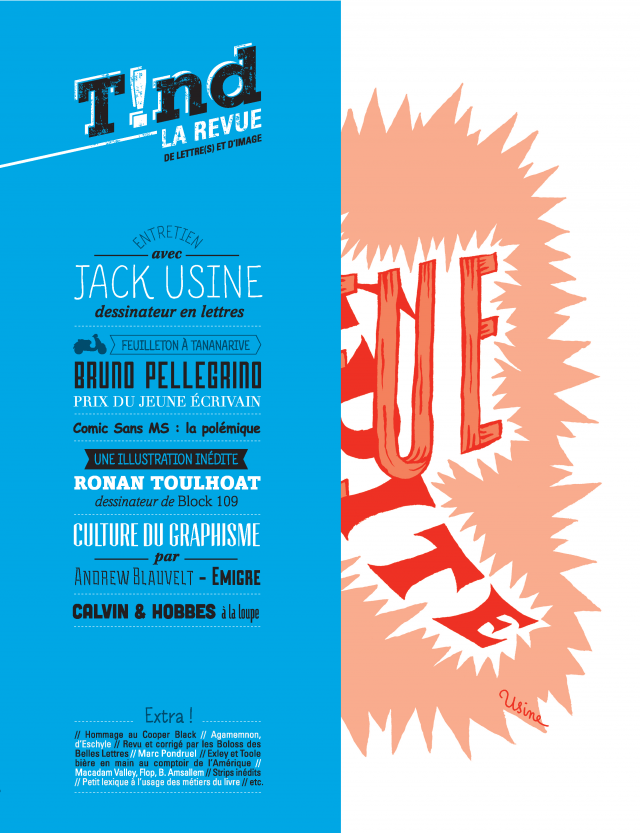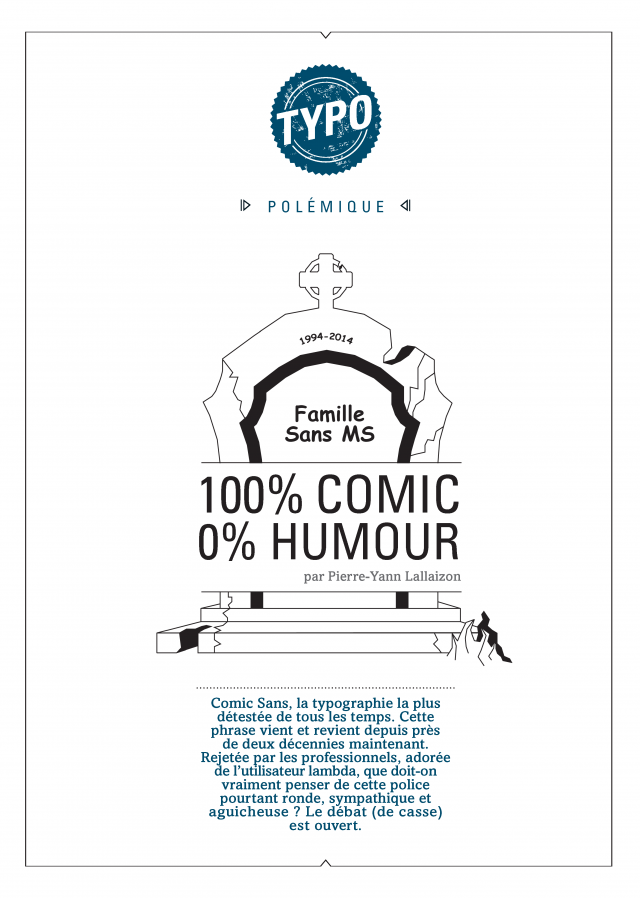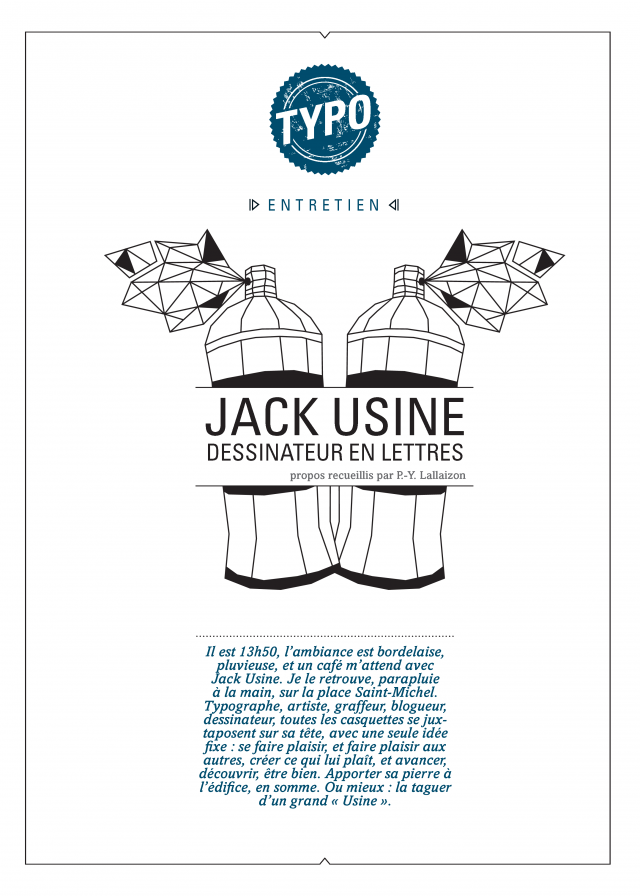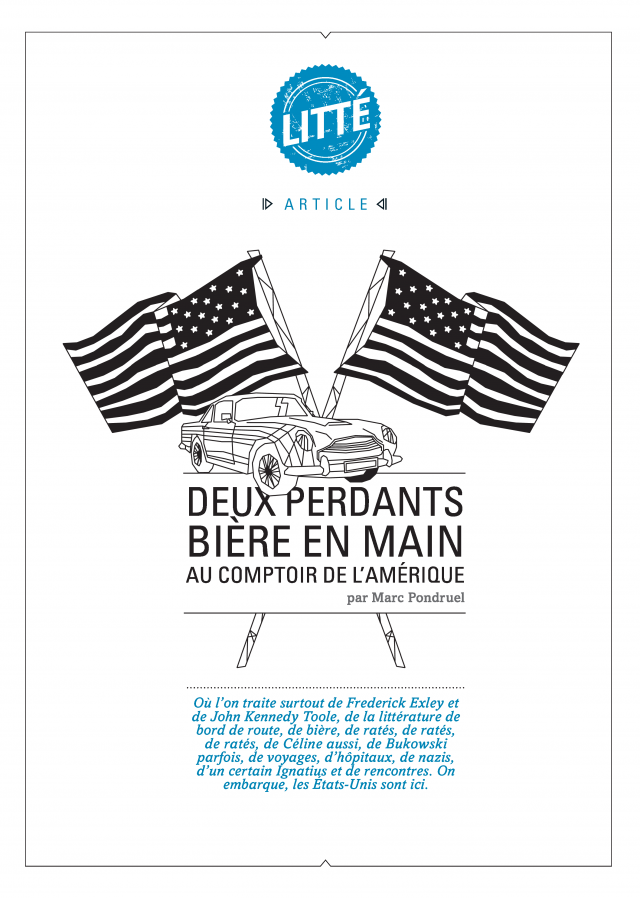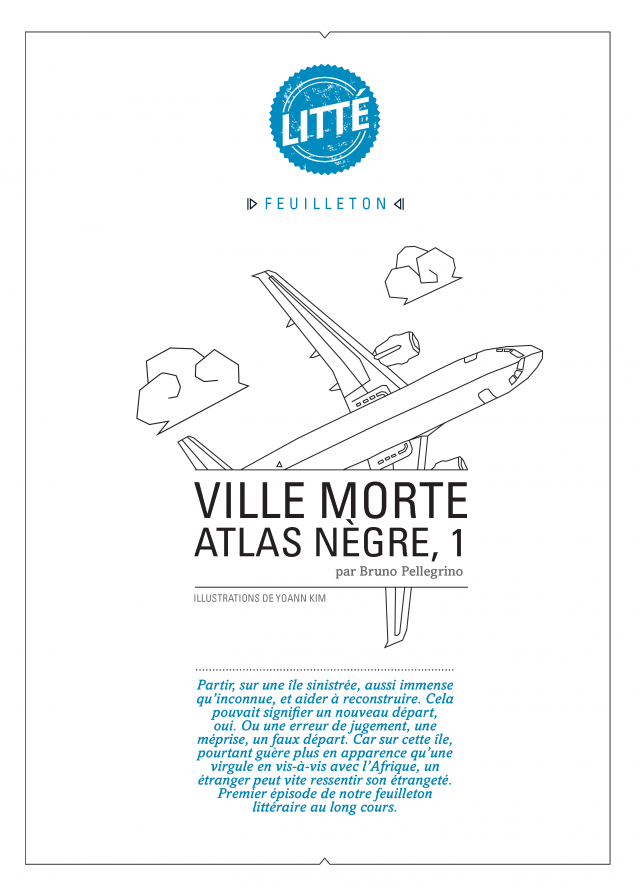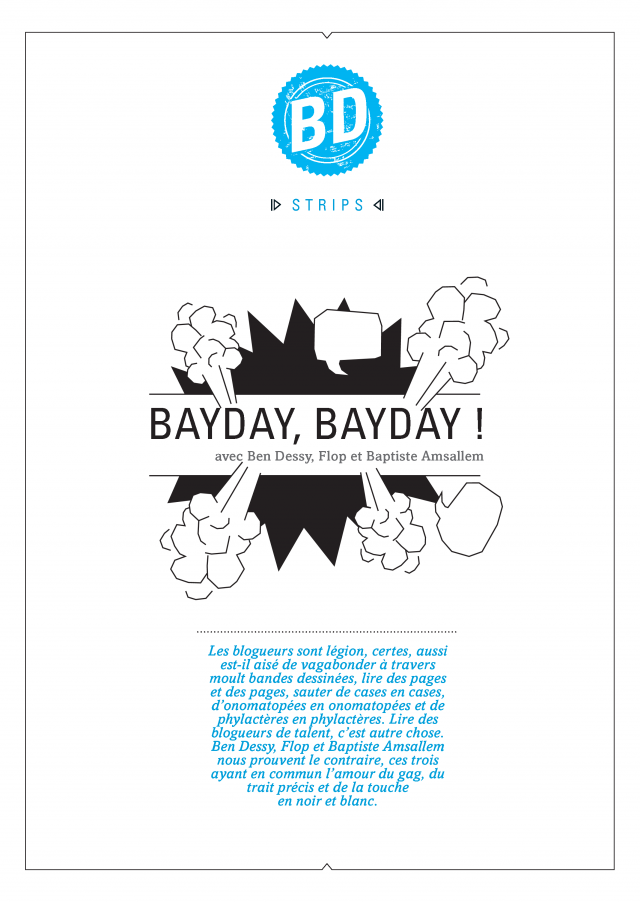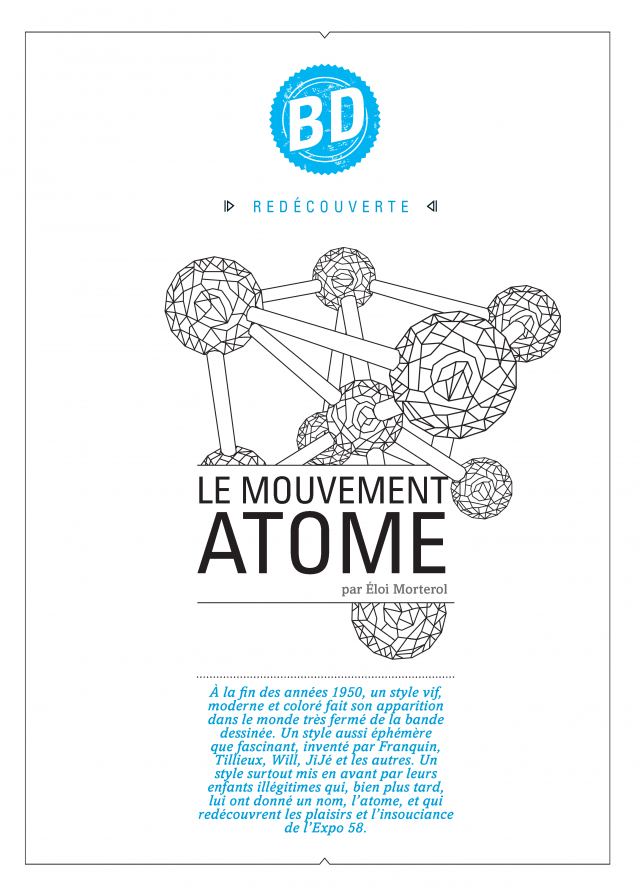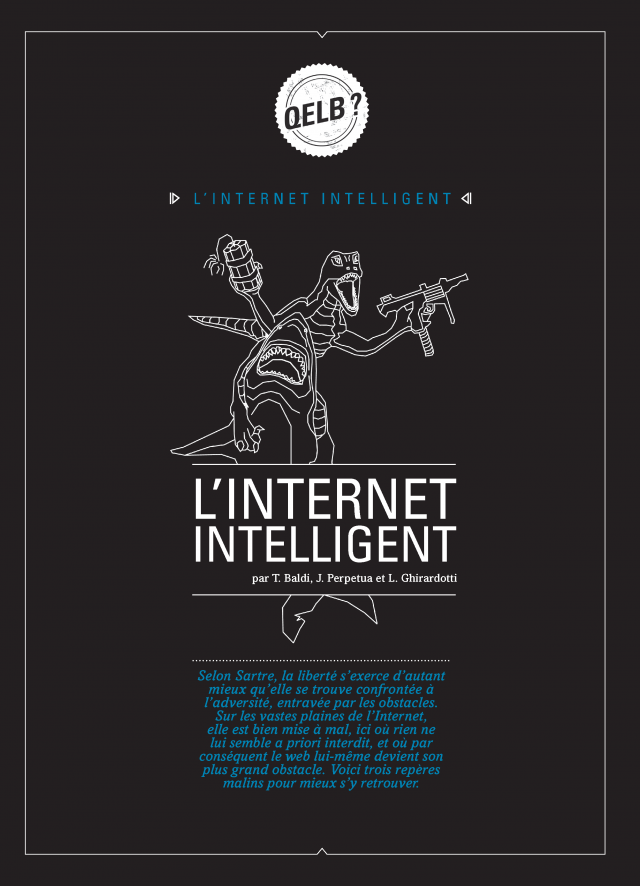
Tind (Typographie is not dead) est une revue de lettre(s) et d’images qui aborde les domaines de la littérature, la bande dessinée, et du typographisme (néoligisme séduisant s’il en est). Imprimée sur beau papier, quadrimestrielle, 112 pages intérieures en bichromie noire et bleue accompagnées d’une maquette soignée. Mais surtout chaque article dispose d’une illustration polygonale comme ouverture. Pour le plaisir des yeux voici celles de Tind #1 : Pépite Bleue.